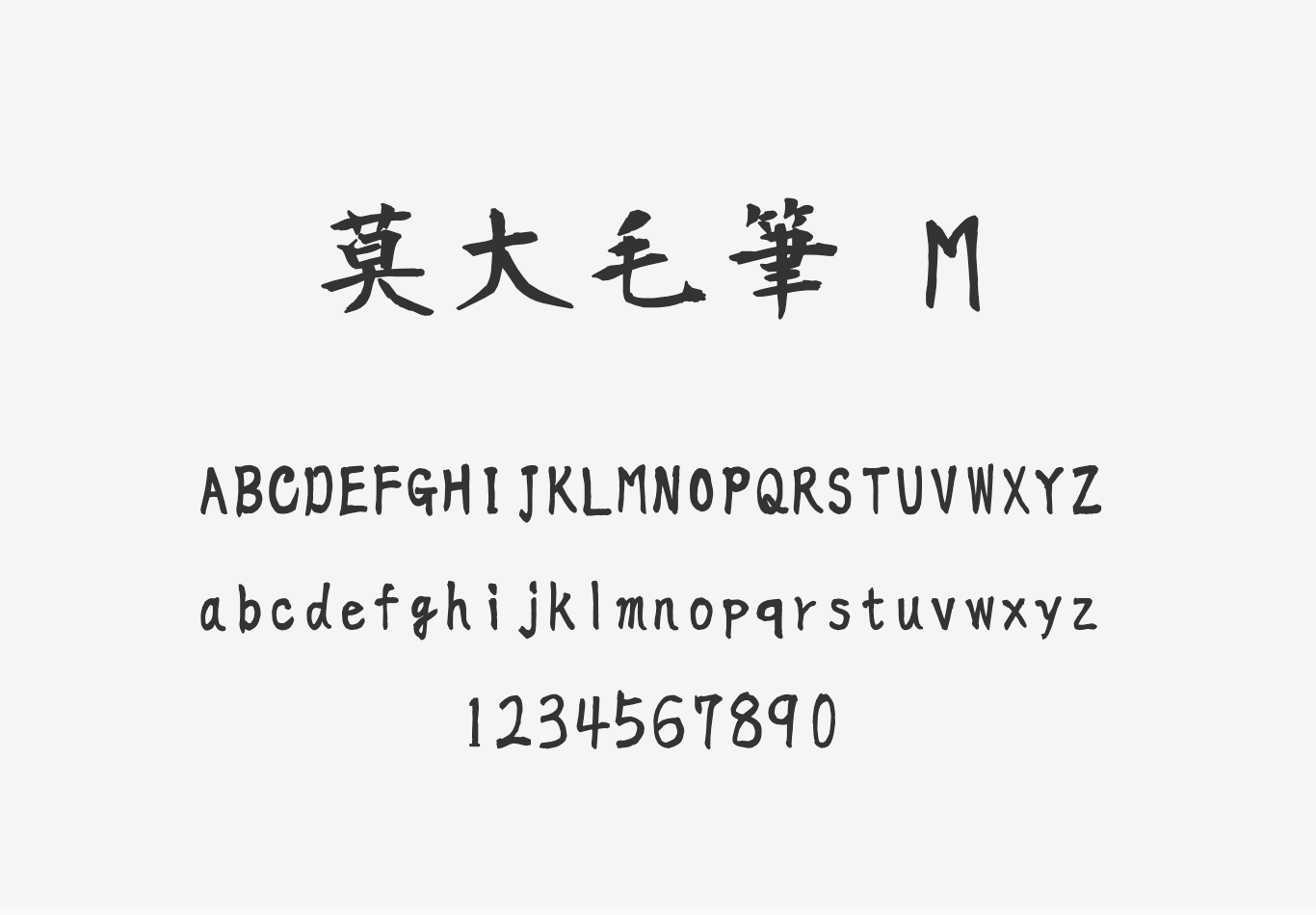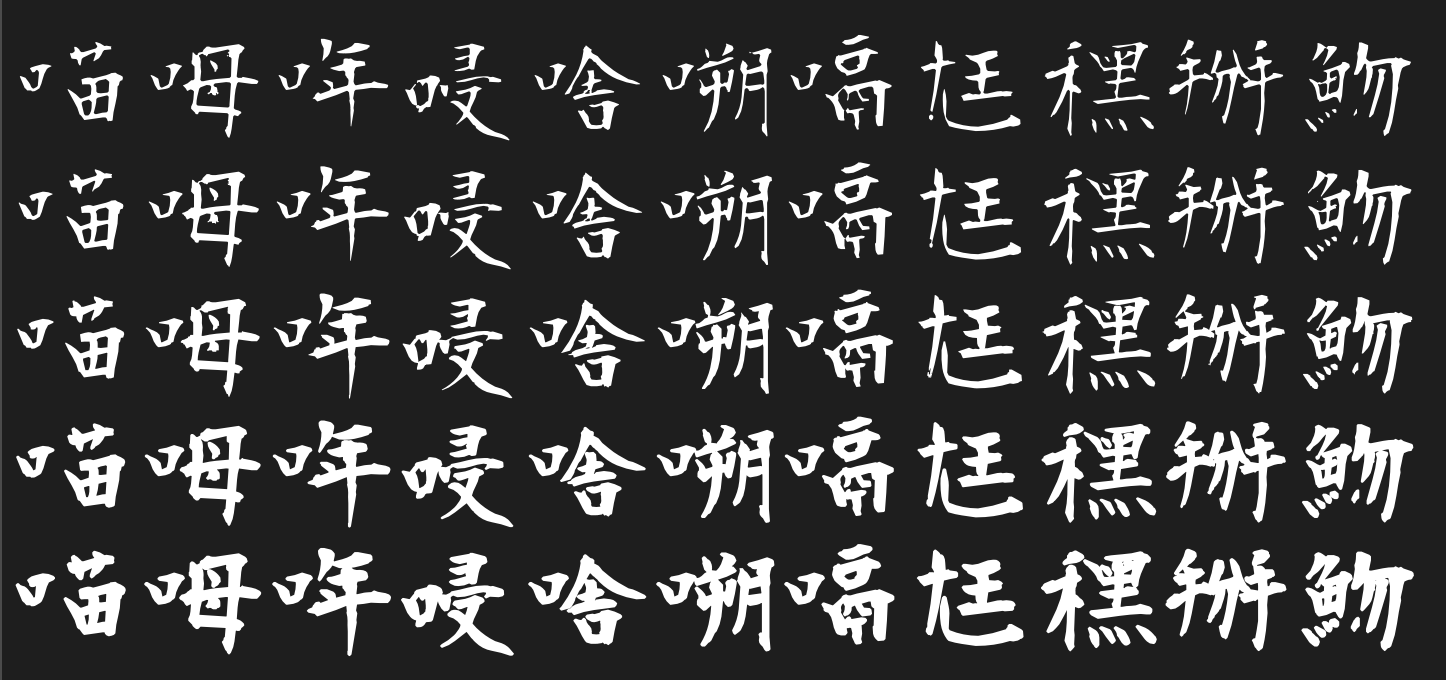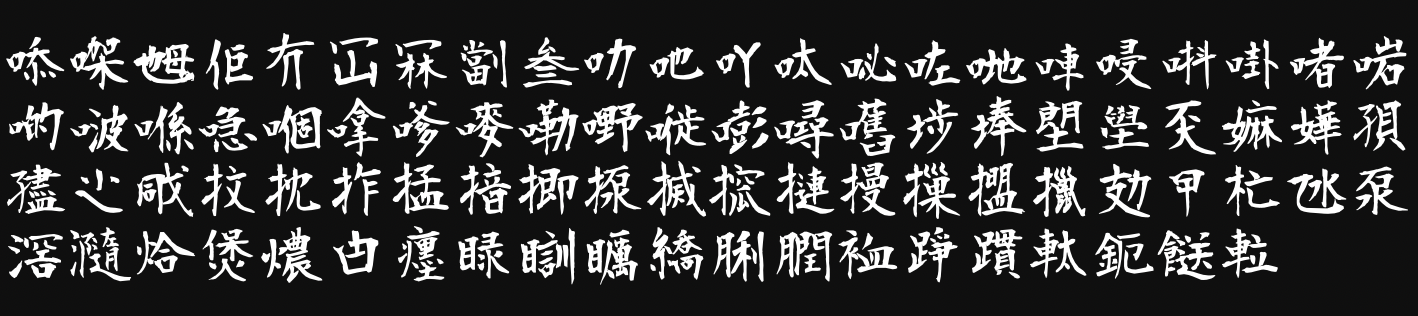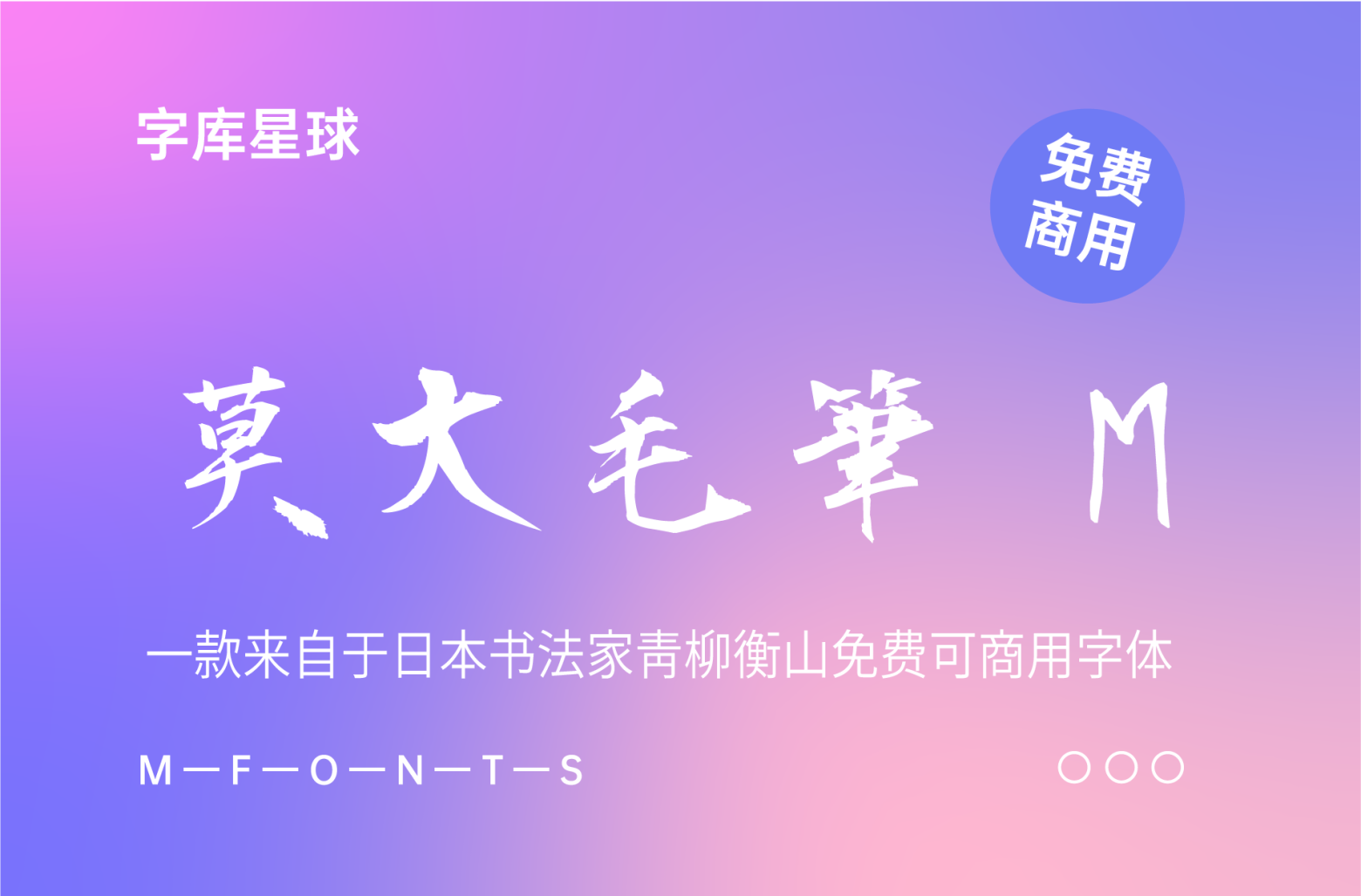
莫大毛笔体(莫大毛筆)是台湾字体爱好者Max基于开源的日本衡山毛笔体(衡山毛筆フォント)增加更多字重及字数的修改版字体。衡山毛笔字体是来自于日本书法家青柳衡山,目前字型内文字和符号字数14321个。
与衡山毛笔体体有何不同?
1、增加了更多中文字体
莫大毛笔体补齐台湾教育部列出的4,808个常用字,在原本的衡山毛笔字体架构下,莫大毛笔字体增加(和修改)168个字。
2、增加了字体字重,现在总共5个字重
原本的衡山毛笔字体放在Regular字重裡,现在透过程序自动产生ExtraLight、Light、Medium、Bold 新的字重。Light字重是把原本的KouzanBrushFont微微调细一点点。在ExtraLight的字重裡,可能会因为笔划太细造成某些笔画消失。在Medium和Bold的字重裡,可能会因为笔划太粗造成某些笔画重叠难以识别,有粗体字的需求,可以先挑战使用Bold字重看看,如果发现效果不如预期,再改用Medium字重。
不能确定自动产生出来的字重裡每一个都是完整的字,毕尽程式会误判是常有的事情,所以不是在Regular字重裡的笔划可能会消失。
3、清除衡山毛笔字体裡空白的文字
衡山毛笔字体裡有很多空白的字, 会造成无法让系统自动用预设字体来补字,已清除空白的文字。
4、调整标点符号位置
衡山毛笔字体的全形标点符号针对日本做设计,调整为台湾常见的置中用法。半形的backslash,调整为非日本地区用法。
5、增加部分台湾口语出现的中文字和增加部份的粤语字
字体展示